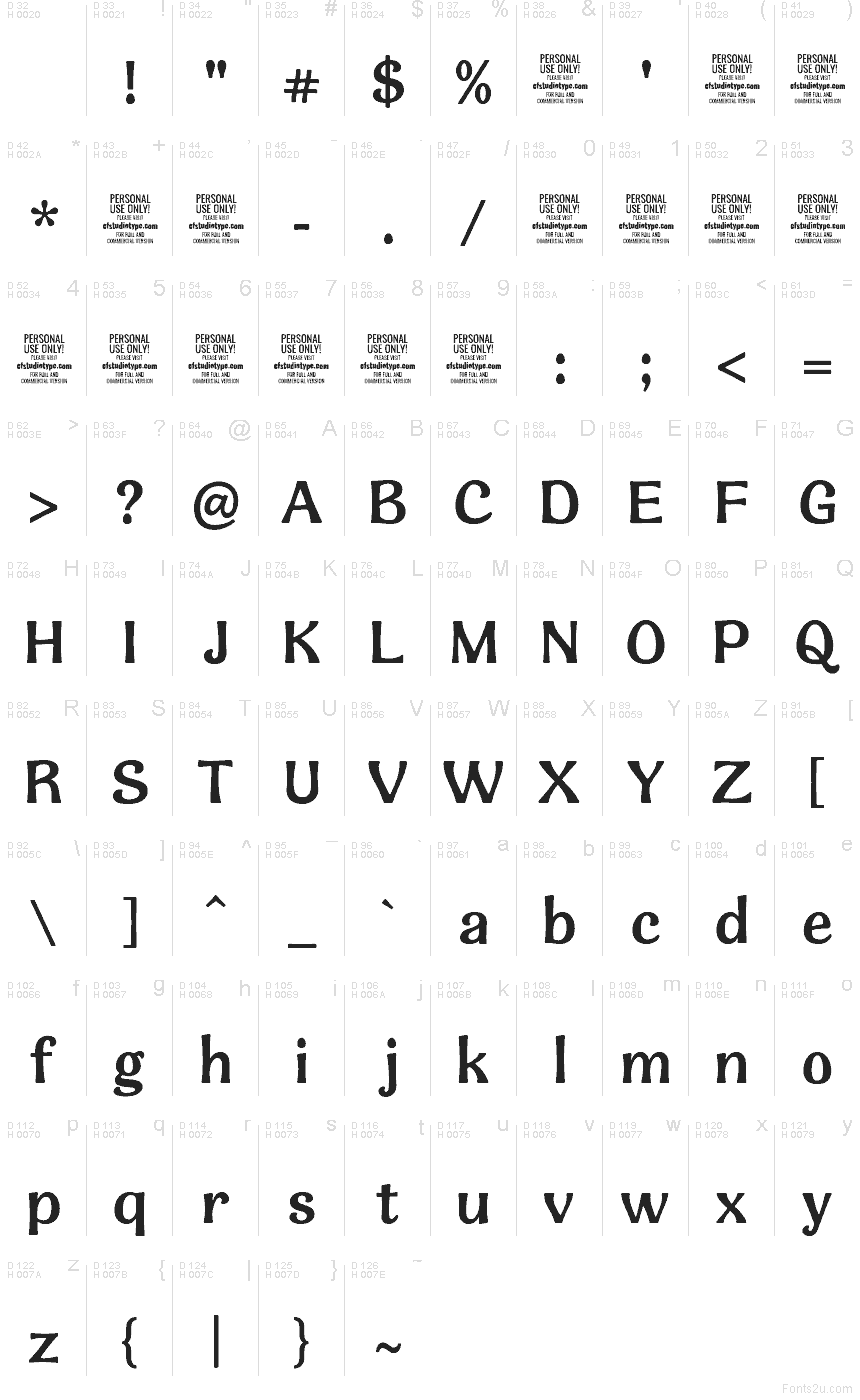
Triorange - Personal Use Bold
Triorange, créée par Ef_Studio, est une police display rétro gratuite aux formes douces et arrondies, dotée d'un rythme amical évoquant le dessin à la main. Ses lettres sont larges et fluides, avec des formes simples qui permettent d'intégrer facilement ce design dans des visuels inspirés du vintage.
Triorange est parfaite pour les titres d'affiches, l'identité visuelle de cafés, le packaging, les visuels pour réseaux sociaux et les logos courts, car sa structure incurvée confère à chaque mot une atmosphère décontractée et nostalgique. Cette police gratuite convient également aux accents éditoriaux et à la signalétique d'événements lorsque vous recherchez un style display marqué qui reste informel sans jamais paraître désordonné.